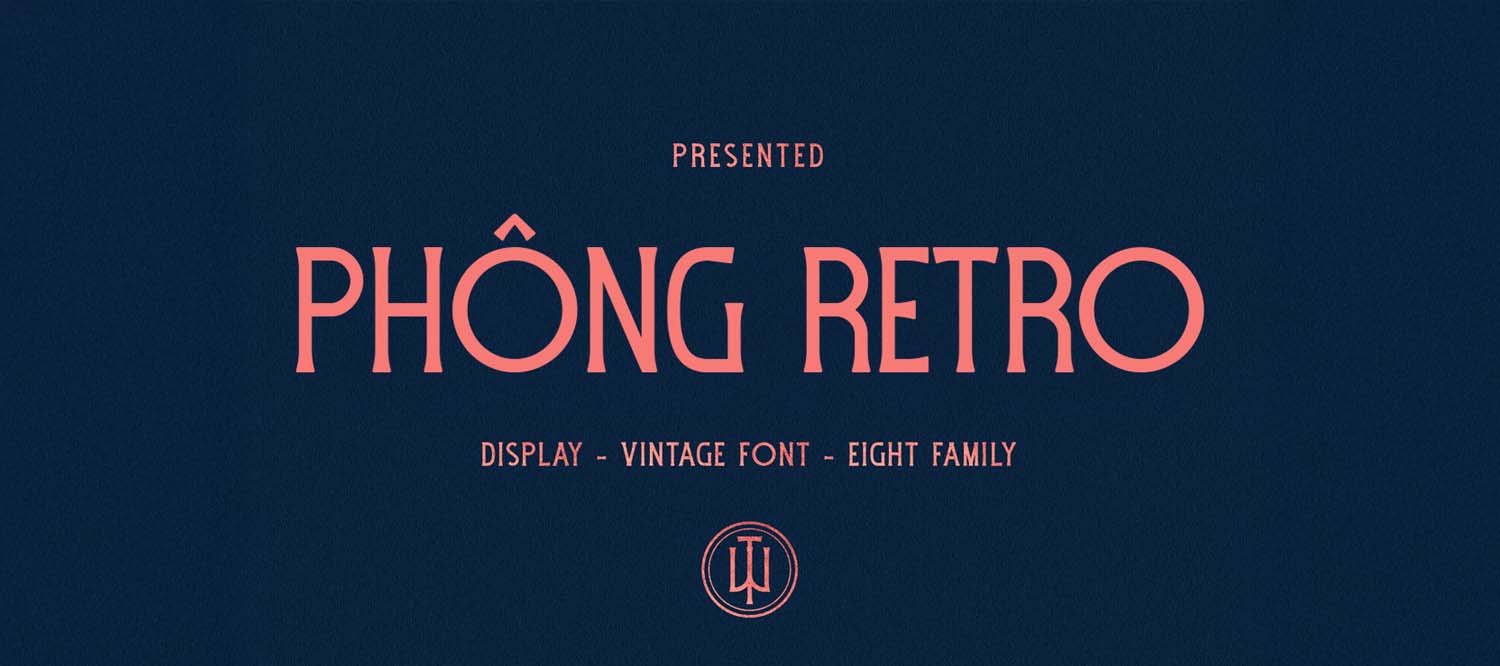
Font chữ retro đang trở thành xu hướng thiết kế nổi bật trong năm 2025, nhờ khả năng gợi lại cảm xúc hoài cổ và thẩm mỹ nghệ thuật độc đáo. Đặc biệt, các bộ font chữ retro Việt hóa đang ngày càng được ưa chuộng bởi sự tiện dụng, dễ dùng trong cả in ấn và digital, đồng thời hỗ trợ đầy đủ tiếng Việt.
Font chữ retro là những kiểu phông lấy cảm hứng từ các phong cách thiết kế trong quá khứ, phổ biến trong giai đoạn từ thập niên 50 đến 90. Các font này thường sở hữu đường nét táo bạo, kiểu dáng nghệ thuật và tạo cảm giác “trở về quá khứ” một cách có chủ đích.
So với vintage – thiên về cảm giác cũ kỹ, và modern – hướng đến sự tối giản, thì retro nổi bật với tính cá nhân, phá cách, và mang màu sắc hoài niệm rõ rệt.
Dưới đây là những font chữ Retro Việt hóa đẹp nhất 2025:
TH Chiffone Regular – Font chữ serif phong cách retro thanh lịch
TH Chiffone Regular mang phong cách serif cổ điển kết hợp nét hiện đại, với các đường nét mềm mại, bo cong tinh tế ở phần chân chữ. Kiểu dáng chữ thon gọn, cao ráo, tạo cảm giác vừa sang trọng vừa hoài cổ. Font rất thích hợp cho tiêu đề tạp chí, poster thời trang vintage hoặc thiết kế branding mang nét quý phái.
TH Manthone – Font chữ retro phá cách và cá tính
TH Manthone sở hữu kiểu dáng đậm, góc cạnh, xen lẫn bo tròn nhẹ – mang hơi hướng retro graphic của thập niên 70s. Các chữ cái được thiết kế phá cách, tạo cảm giác mạnh mẽ và nổi bật ngay từ cái nhìn đầu tiên. Rất phù hợp cho thiết kế tiêu đề, poster nghệ thuật, hoặc biển hiệu phong cách cổ điển nhưng hiện đại.
MTD Yerington – Font retro đậm chất báo chí & thương hiệu hoài cổ
MTD Yerington có kiểu chữ slab serif mạnh mẽ, đường nét dày dặn, dễ đọc và tạo điểm nhấn ngay khi sử dụng. Phong cách hoài cổ gợi nhớ đến typography của các tờ báo hoặc bảng quảng cáo thập niên 60. Phù hợp cho thiết kế logo retro, nhãn bao bì sản phẩm truyền thống, hoặc tiêu đề mang tính thương hiệu.
TH Neue Yokarto – Font chữ retro cổ điển mang tính nghệ thuật
TH Neue Yokarto gây ấn tượng với kiểu dáng decorative serif kết hợp các nét móc cầu kỳ và chi tiết trang trí. Phong cách mang hơi thở Art Nouveau – cổ điển, mềm mại nhưng đầy tính nghệ thuật. Đây là lựa chọn lý tưởng cho bìa sách, poster phim hoài cổ hoặc thương hiệu mang yếu tố văn hóa.
TH Clarineto – Font retro mang hơi hướng lịch sử & báo chí xưa
TH Clarineto mang hình dáng serif chắc chắn, cổ điển, gợi nhớ đến bảng tiêu đề của báo chí châu Âu đầu thế kỷ 20. Các đường nét có độ tương phản cao, tạo cảm giác sang trọng và có chiều sâu lịch sử. Rất phù hợp để dùng trong thiết kế editorial, tiêu đề tạp chí, hoặc các dự án branding cổ điển.
TH Sink – Font chữ retro bo tròn mang phong cách vui tươi
TH Sink mang phong cách retro sans-serif bo tròn, dễ thương và mang cảm giác mềm mại, gần gũi. Font có nét hơi hướng thiết kế thập niên 80, phù hợp cho thiết kế poster vui nhộn, tiêu đề social media, hoặc branding trẻ trung mang tinh thần hoài cổ hiện đại.
TH Juggernaut – Font chữ retro lịch sử mạnh mẽ và ấn tượng
TH Juggernaut là kiểu chữ sans-serif mang phong cách retro lịch sử, được thiết kế với đường nét mạnh mẽ, góc cạnh và hình học cổ điển. Các ký tự có cấu trúc chắc chắn, tạo cảm giác vững chãi, nghiêm túc và rất phù hợp với các thiết kế poster, tiêu đề sự kiện hoặc dự án mang tính cổ điển, công nghiệp.
TH Wible Town – Font serif cổ điển, mềm mại và trang trọng
TH Wible Town mang phong cách serif cổ điển với đường nét uốn cong nhẹ nhàng, tạo cảm giác hoài niệm và thanh lịch. Các chi tiết trang trí được xử lý tinh tế, phù hợp với các thiết kế như bìa sách, thiệp mời, logo thương hiệu mang phong cách vintage hoặc châu Âu cổ.
TH Holywest – Font western retro gợi nhớ miền Tây hoang dã
TH Holywest là kiểu chữ serif đậm chất western với các nét chữ dày, góc bo nhẹ và cảm hứng từ bảng hiệu saloon miền Tây nước Mỹ. Thiết kế mang lại cảm giác vừa mạnh mẽ vừa cổ điển, thích hợp cho các dự án branding cá tính, poster phim, quán bar hoặc bao bì thủ công.
TH Kagestone – Font retro cổ điển với nét serif sắc sảo
TH Kagestone là một font serif mang đậm dấu ấn cổ điển với các chi tiết nét cắt sắc gọn, độ tương phản cao và kiểu dáng gợi nhớ đến typography thế kỷ 20. Phù hợp cho tiêu đề báo chí, thiết kế branding lịch sử hoặc các dự án cần sự kết hợp giữa cổ kính và hiện đại.
TH Mackenzin – Font serif cổ điển, thanh lịch và chuyên nghiệp
TH Mackenzin mang phong cách serif hoài cổ, với kiểu chữ thanh mảnh, cao ráo và độ tương phản vừa phải. Thiết kế này gợi nhớ đến các font chữ in trong sách cổ, rất phù hợp cho các dự án cần tính lịch sử, cổ điển hoặc sử dụng trong thiết kế văn hóa – nghệ thuật.
TH Castio – Font serif đậm chất cổ điển, mạnh mẽ và vững chắc
TH Castio là một font chữ có chân (serif) với kiểu dáng đậm nét, cấu trúc vuông vức và sắc cạnh. Phong cách thiết kế của font này mang hơi hướng hoài cổ nhưng vẫn rõ ràng và hiện đại, phù hợp cho tiêu đề tạp chí, thiết kế poster hoặc logo cần tạo ấn tượng trang trọng và cổ điển.
Đồ họa: Icon thủ công, hoạ tiết retro, viền bo tròn cổ điển